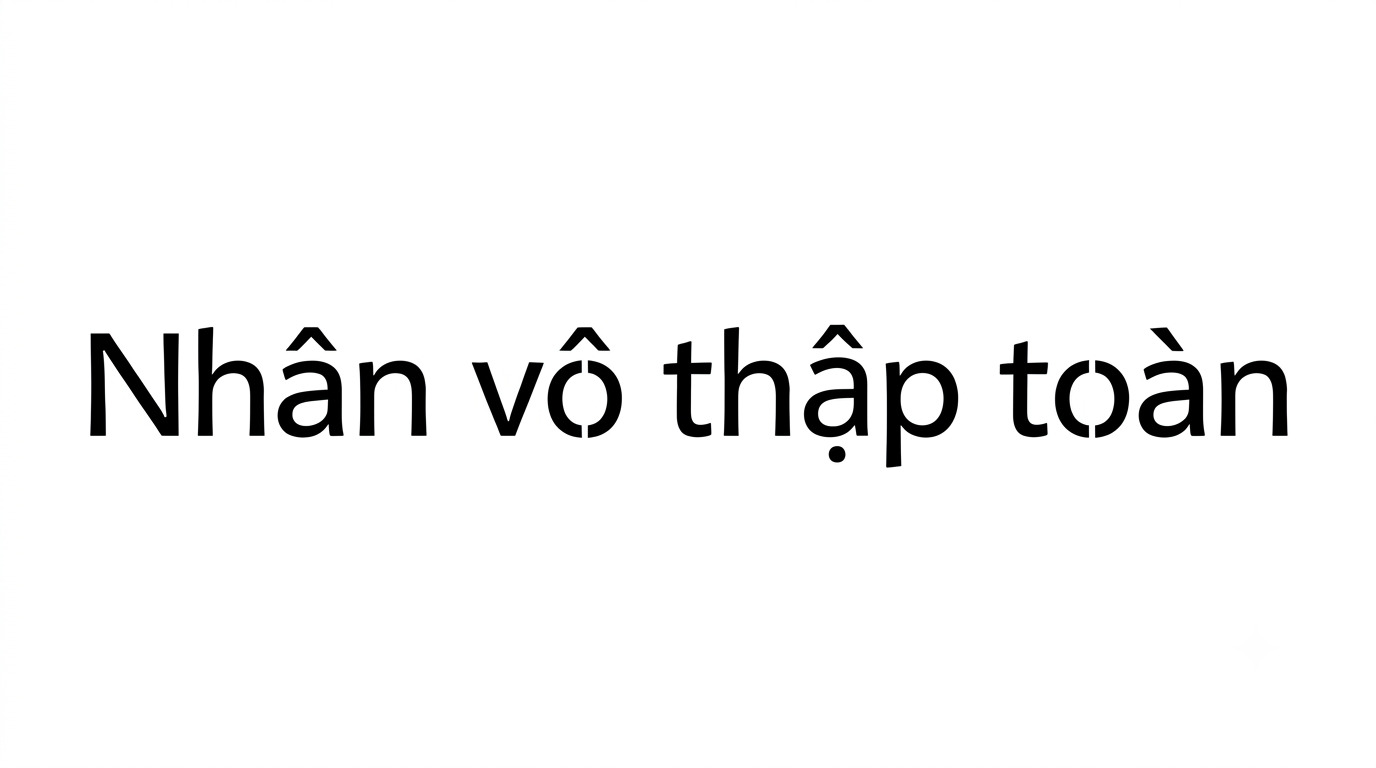
Nhiều designer khi sử dụng Hanson font thường gặp tình trạng thiếu dấu tiếng Việt hoặc nét chữ bị vỡ khi phóng lớn để in trên bao bì, hộp quà và các ấn phẩm thương hiệu. Những lỗi này có thể làm bố cục thiết kế thiếu đồng nhất và ảnh hưởng đến tính chuyên nghiệp của thành phẩm.
Font Hanson là gì?
Font Hanson là một bộ phông chữ thuộc dòng Sans-serif hiện đại, gây ấn tượng mạnh mẽ nhờ cấu trúc chữ cực kỳ dày (bold), vững chãi và mang đậm hơi hướng tương lai (futuristic). Đặc trưng của Hanson là những đường nét hình học dứt khoát, các góc vát sắc sảo tạo nên vẻ ngoài đầy nội lực và quyền uy. Đây là lựa chọn cho các thiết kế logo công ty khởi nghiệp công nghệ, tiêu đề poster phim hành động, bao bì thiết bị điện tử hoặc các biển hiệu trụ sở tập đoàn yêu cầu sự trực diện.
Trong giới đồ họa đương đại, Hanson được ưa chuộng bởi khả năng thu hút thị giác cực mạnh ngay từ cái nhìn đầu tiên. Tuy nhiên, do cấu trúc chữ mang tính hình học khắt khe, Hanson thường gặp khó khăn khi xử lý các dấu thanh tiếng Việt sao cho không bị “thô” hay lệch tông so với các ký tự gốc. Bản hanson font việt hóa tại In Viva đã được tinh chỉnh kerning, đảm bảo các ký tự có dấu hiển thị mượt mà, giúp bản thiết kế của bạn luôn sang trọng và đồng nhất trên mọi chất liệu.
Bảng kí tự font Hanson
Lưu ý: Hanson mang phong cách tối giản và mạnh mẽ. Khi sử dụng cho in ấn trên bao bì hộp quà cao cấp, bạn nên phối hợp với các tông màu đen – trắng hoặc bạc kim loại để tôn lên vẻ đẹp hiện đại của bộ chữ.
5 ứng dụng của font Hanson trong thiết kế và in ấn quà tặng
Với kiểu chữ dày, khỏe và mang phong cách hiện đại, Hanson có thể ứng dụng trên nhiều loại bao bì và quà tặng doanh nghiệp, đặc biệt là các thiết kế cần tạo điểm nhấn rõ ràng cho tên thương hiệu hoặc logo:
• Thiết kế bao bì thiết bị điện tử và linh kiện: Hanson phù hợp để thể hiện tên thương hiệu, tên sản phẩm hoặc slogan trên hộp cứng đựng tai nghe, sạc dự phòng và đồng hồ thông minh. Nét chữ dày giúp nội dung nổi bật trên bố cục bao bì công nghệ.
• Sản xuất set quà tặng văn phòng in logo: Logo sử dụng font Hanson có thể in UV hoặc khắc laser trên bình giữ nhiệt, sạc dự phòng, sổ tay và các phụ kiện văn phòng. Kiểu chữ gọn, khỏe phù hợp với các bộ quà tặng mang phong cách trẻ và hiện đại.
• In túi giấy thương hiệu công nghệ: Hanson có thể sử dụng cho tên thương hiệu hoặc tiêu đề chính trên túi giấy Ivory, giấy mỹ thuật. Với phần chữ phụ như địa chỉ, website hoặc thông tin liên hệ, nên kết hợp cùng font có nét mảnh hơn để tạo phân cấp nội dung.
• Trang trí bảng hiệu và không gian showroom: Khi được chuyển sang định dạng vector, Hanson có thể phóng lớn để sử dụng trên bảng hiệu, backdrop hoặc khu vực trưng bày mà vẫn giữ cấu trúc đường nét của chữ.
• Sản xuất kỷ niệm chương và vật phẩm vinh danh: Hanson Bold phù hợp để thể hiện tên doanh nghiệp, tên chương trình hoặc mốc kỷ niệm trên kỷ niệm chương pha lê và kim loại. Nét chữ dày cũng thuận lợi khi cần khắc laser trên một số bề mặt phù hợp.
Font Hanson đẹp 01
5 lưu ý khi sử dụng font Hanson
Hanson sở hữu nét chữ khá dày nên khi đưa từ thiết kế lên thành phẩm, designer cần kiểm soát kích thước, khoảng cách và kỹ thuật gia công để hạn chế tình trạng chữ bị bít hoặc mất chi tiết.
• Kiểm soát độ dày của nét chữ: Với các ký tự có khoảng âm nhỏ như “a”, “e” hoặc “o”, không nên thu chữ xuống kích thước quá nhỏ. Trước khi sản xuất số lượng lớn, designer nên in test ở kích thước thực tế để kiểm tra khả năng đọc và mức độ bít nét.
• Tối ưu đường Path khi dập nổi: Khi dùng Hanson để dập nổi logo trên hộp cứng, các điểm neo và góc trong file vector cần được kiểm tra, loại bỏ những node dư. Đường path gọn giúp quá trình làm khuôn dập nổi thuận lợi hơn và hạn chế ảnh hưởng đến các góc chữ trên giấy mỹ thuật.